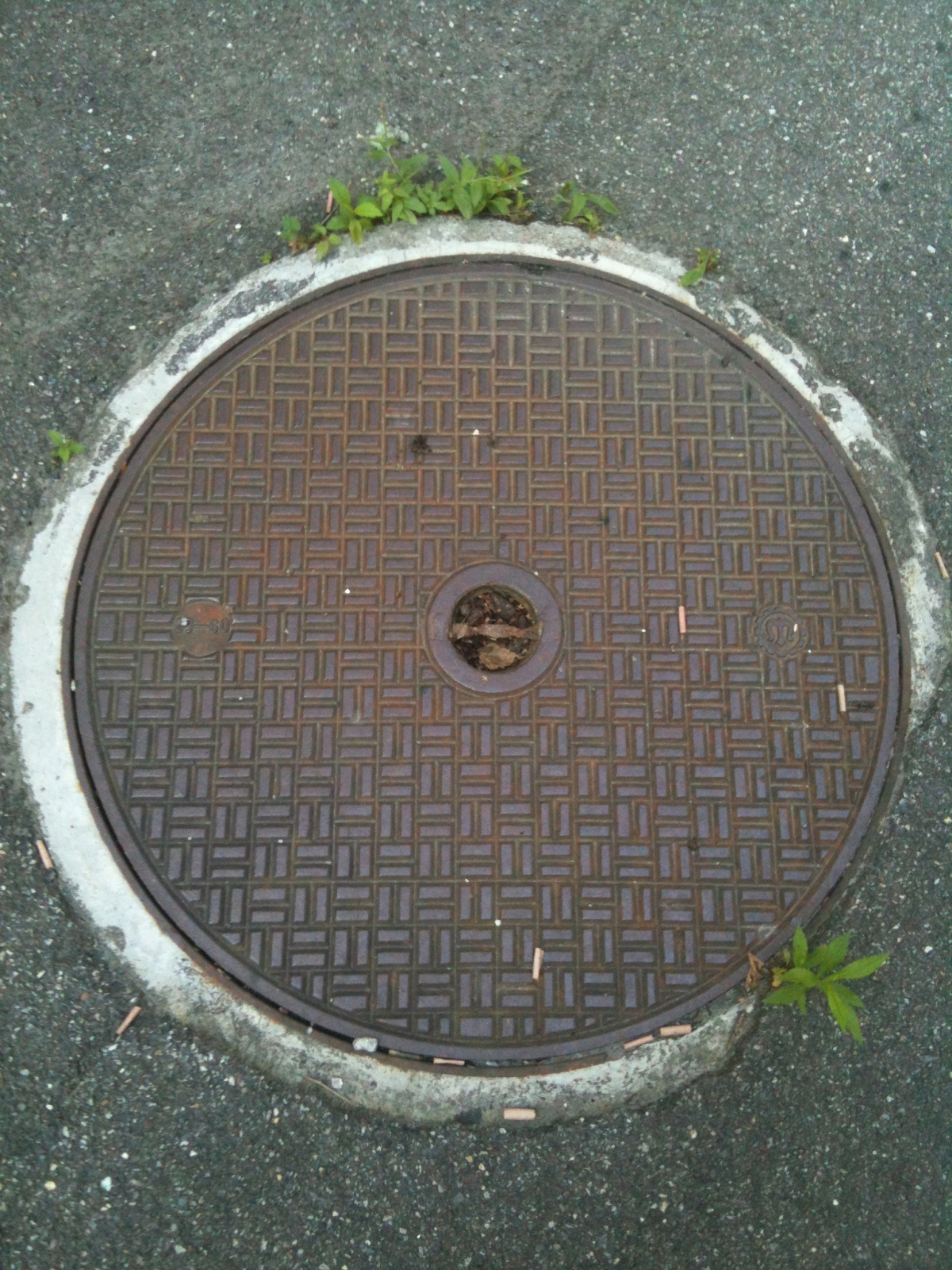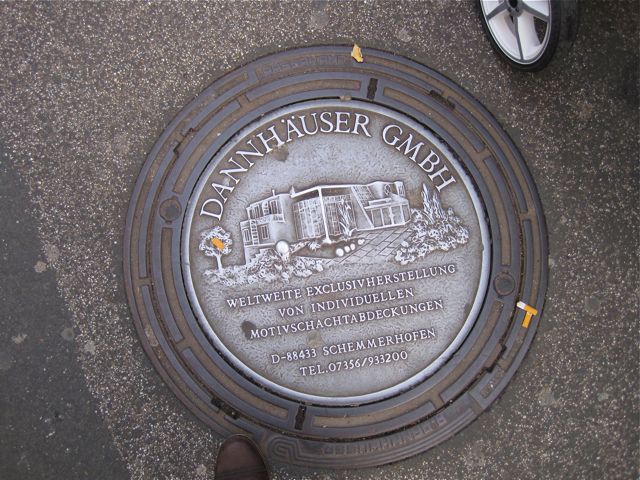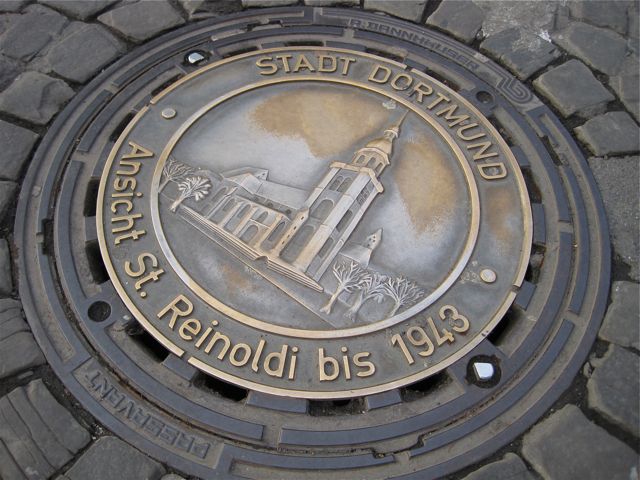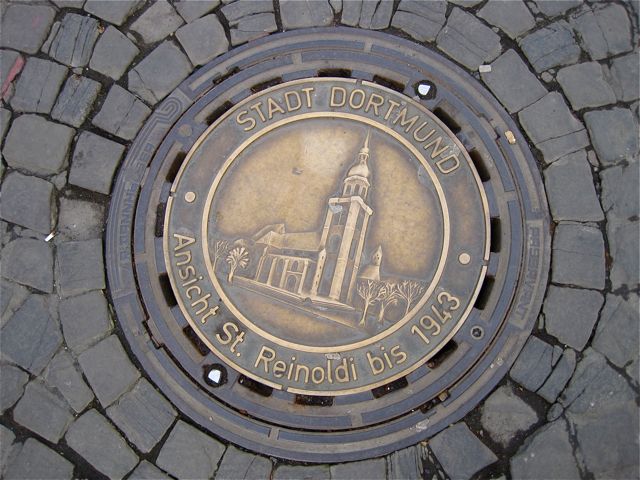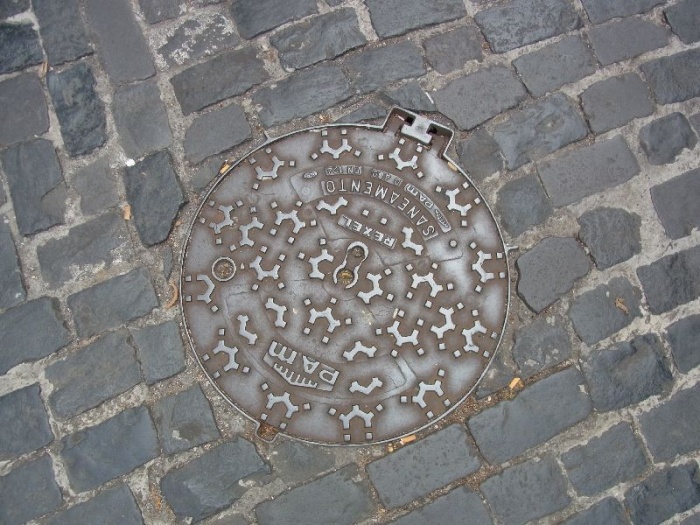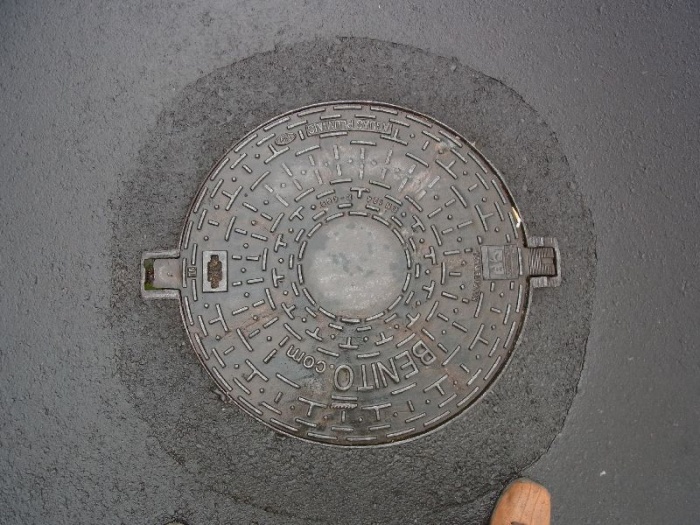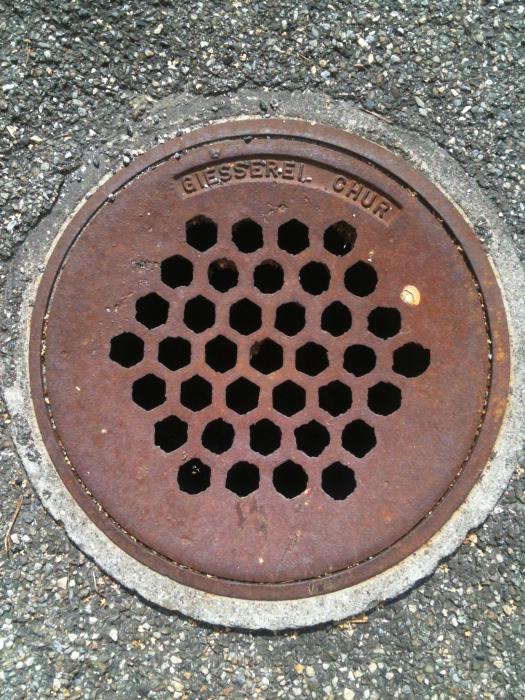
genau. es geht hier herum ja um schmachtdeckel. ;)
Zum Kerning der Photographin kann ich nichts sagen, aber die O von Timmendorf und Niendorf stehen doch ziemlich einsam in der holsteinschen Landschaft.
Zugegeben: Drainspotting war jetzt nicht meine Priorität im Urlaub, und ich habe keine außergewöhnlichen Deckel per Zufall entdeckt, aber zwei Standard-Deckel habe ich doch mitgebracht:
Einen von Funchal, der Hauptstadt von Madeira:
Und einen von São Vicente (mit Qualitätsschuh :hammer: ):
Am Wahlsonntag luden mich freundliche Menschen spontan in ihren Garten ein, um ihre Kanaldeckel zu fotografieren (sie hatten sich gewundert, warum ich so interessiert über ihren Zaun geschaut habe). Sie erzählten mir ganz begeistert, dass sie beim Hausbau die Deckel selber gekauft haben, damit die Gemeinde in ihrem Garten keine schnöden Betondeckel verlegt. Die Deckel haben übrigens 180 € das Stück gekostet. Wieder was gelernt!  ;-)
hatten wir die schon mal? (alle chur, schweiz)
Witzig. Vor ein paar Minuten habe ich das vonRoll-Museum angeschrieben, um herauszufinden, was es mit dem Zeichen auf sich hat, das Du hier zeigst. Es ist auf vielen Deckeln der Firma vonRoll zu sehen.
würd’ das dann sehr gern erfahren, wenn mal eine antwort anrollt.
Bisher habe ich keine Antwort. Ich vermute mal, daß das gar nicht direkt mit vonRoll zusammenhängen muß, sondern das Zeichen einer Materialprüfanstalt sein könnte, habe aber da auch nichts bei den Schweizer Materialprüfanstalten gefunden. Kann natürlich sein, daß das älteren Datums und längst außer Gebrauch ist.
wenn das zeichen einem M nachempfunden wär’? also irgendwas in richtung des französischen "Moulage" …
Ich habe doch vor ewigen Zeiten mal den historischen Sieleingang am Hamburger Baumwall in diesem Thread gepostet. Jetzt hat man dort durch Zufall unterirdisch einen historischen Umkleideraum entdeckt, der 1904 für Wilhelm II. angelegt worden war.
Das geheime Zimmer von Kaiser Wilhelm II. am Baumwall
1904 entstand für Wilhelm II. am Baumwall ein Sieleinstieg und ein unterirdischer Umkleideraum, den man zumauerte. Jetzt wurde er zufällig entdeckt. Hamburg Wasser investierte 28.000 Euro in die Renovierung.
Es gab sogar noch mehr Werbedeckel, aber da in Dortmund heute neben Fußball auch noch so eine Art Faschingskirmes stattfand, bin ich beim Fotografieren fast unter die Räder geraten und wollte die Geduld der Einwohner lieber nicht über Gebühr strapazieren. Zumal ziemlich viele gelb-schwarz gewandete Menschen zielstrebig auf dem Weg ist Stadion waren, als ich meine Fotosafari gemacht habe.  ;-)
Ooch, von unten kann auch ganz nett sein.
Ein Glück, dass meine Tochter mir eben nicht über die Schulter gekuckt hat! Du treibst die Erwartungen an abenteuerliche Kindergeburtstage ja in Höhen, die jenseits von Gut und Böse liegen. :-o